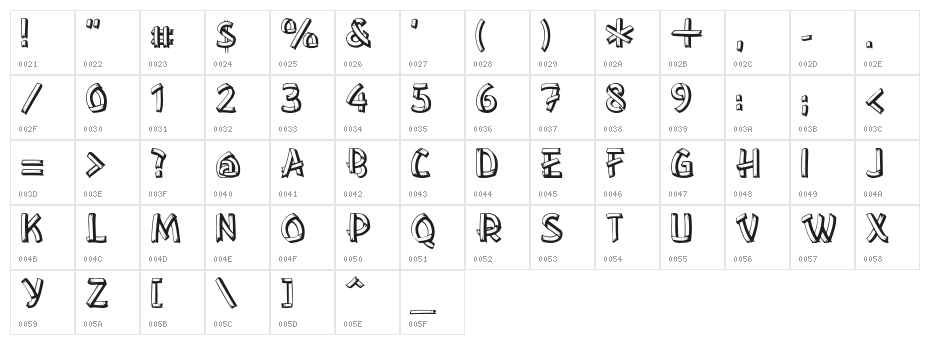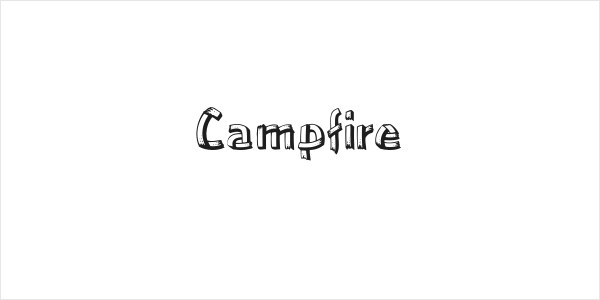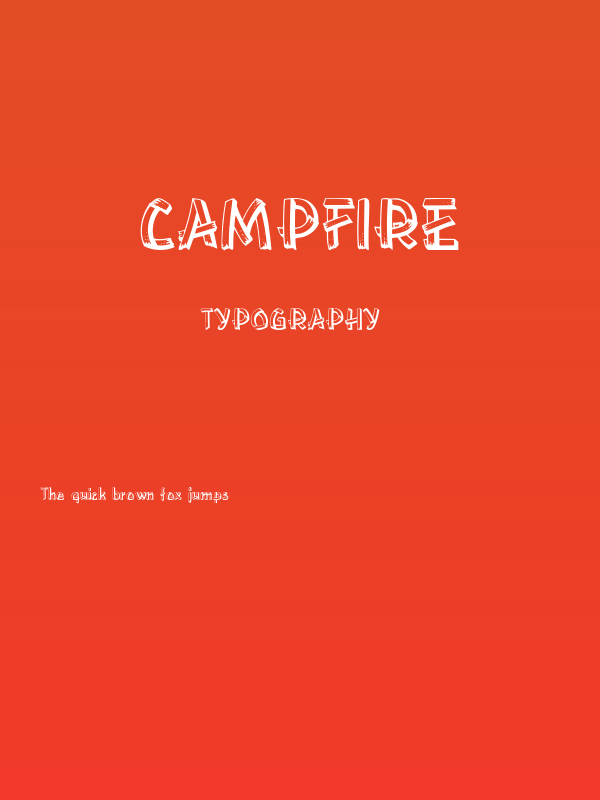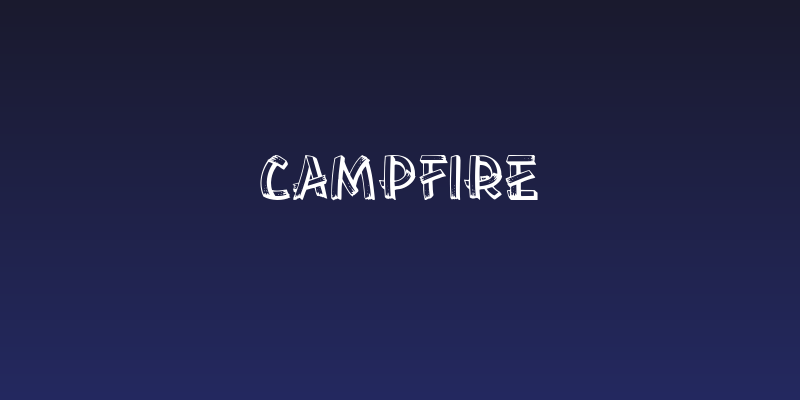
Campfire Font
| Nombre | Campfire |
| Categorías | Outline |
| Estilo general | Rustic, Adventurous, Playful |
| Proyectos propuestos | Perfect for outdoor-themed posters, adventure branding, children's book covers, and rustic event invitations. |